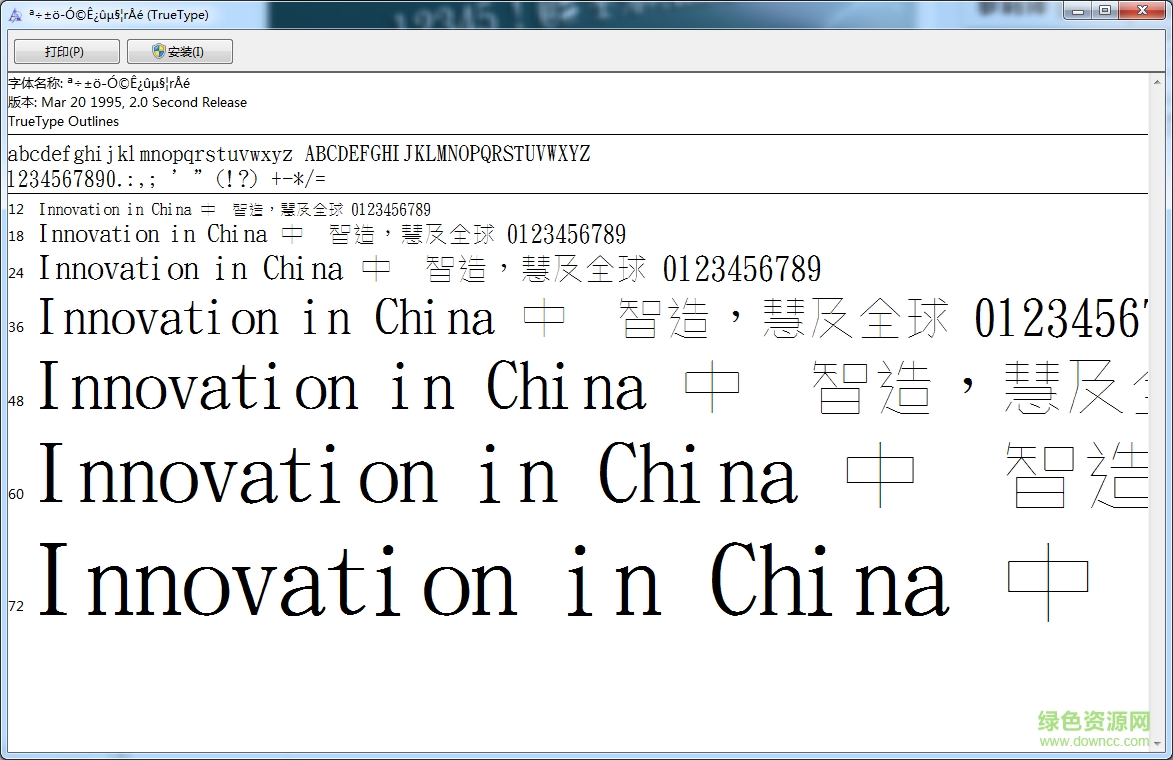
金梅個(gè)性鋼筆字體是金梅字體中別具一格的鋼筆字體,字體纖細(xì)簡(jiǎn)單,極具個(gè)性使用廣泛,深受廣大用戶喜愛??靵砭G色資源網(wǎng)下載體驗(yàn)吧!
金梅個(gè)性鋼筆字體是一款非常實(shí)用的電腦字體,該字體可應(yīng)用于鋼筆字設(shè)計(jì)方面,字體纖細(xì)大方得體,結(jié)構(gòu)端莊,可用于印刷出版、包裝設(shè)計(jì)、廣告設(shè)計(jì)、網(wǎng)頁設(shè)計(jì)、屏幕顯示等,喜歡的小伙伴趕緊下載體驗(yàn)下吧~